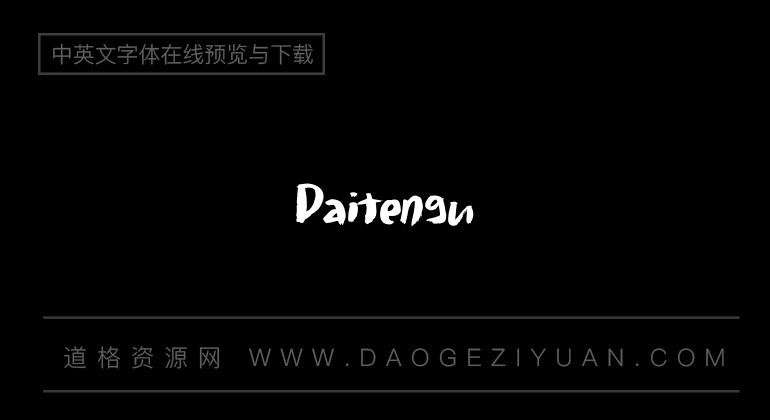
Daitengu 字体是一种免费的日本风格的字体,具有清晰易读的特点。这种字体由日本设计师 Akihiro Oya 设计,是由 OpenType 技术创建的。Daitengu 字体包含日语平假名、片假名、罗马字以及一些特殊字符。它的设计灵感来源于日本传统文化和自然景观,呈现出一种精美的艺术风格。Daitengu 字体适用于广告、印刷品、海报、书籍和网站等多种设计项目。内容介绍
Daitengu是一款非常不错的手写艺术字体,具有很好的视觉感,适合于文化类的宣传设计、商业类品牌的广告和产品包装设计以及个性化文字排版等较多场景。